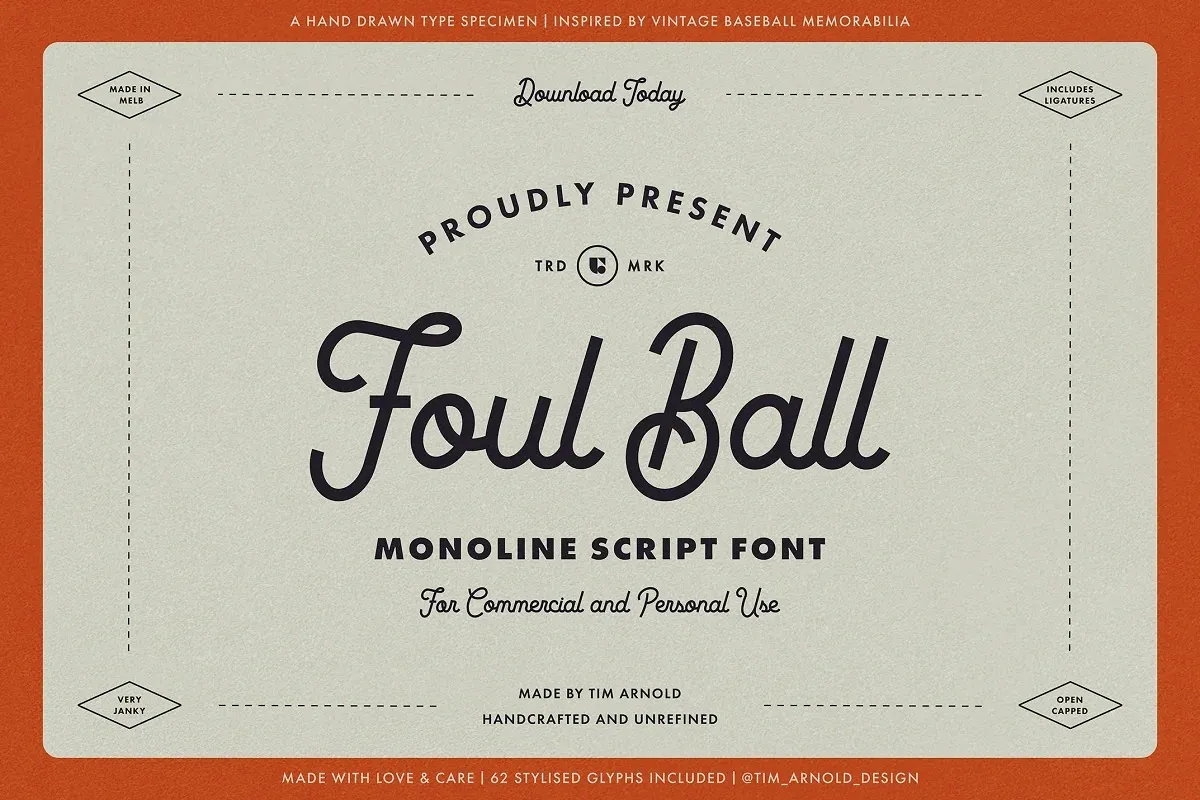
Foul Ball Font – Download Grátis
Esta é uma fonte script inovadora criada pelo tim Arnold Design, perfeita para designers que buscam dar um toque único e retro a seus projetos visuais. Inspirado nos posters vintage dos anos 80, na iluminação neon de antigas estrelas da TV, e nas designs modernas voltadas para o passado, esta fonte pode transformar qualquer headline ou logotipo em uma peça irresistível. Ela é ideal para adicionar um toque retro inigualável a aplicações gráficas variadas, desde roupas até merchandising. Com seu look antigo e cheio de personalidade, esta fonte é perfeita tanto para aqueles que buscam uma aparição moderna, quanto para quem deseja manter um clima nostálgico. Não hesite em experimentar este design único; ele certamente irá enriquecer seus trabalhos visuais e dar um toque de profundidade inesquecível a qualquer projeto.